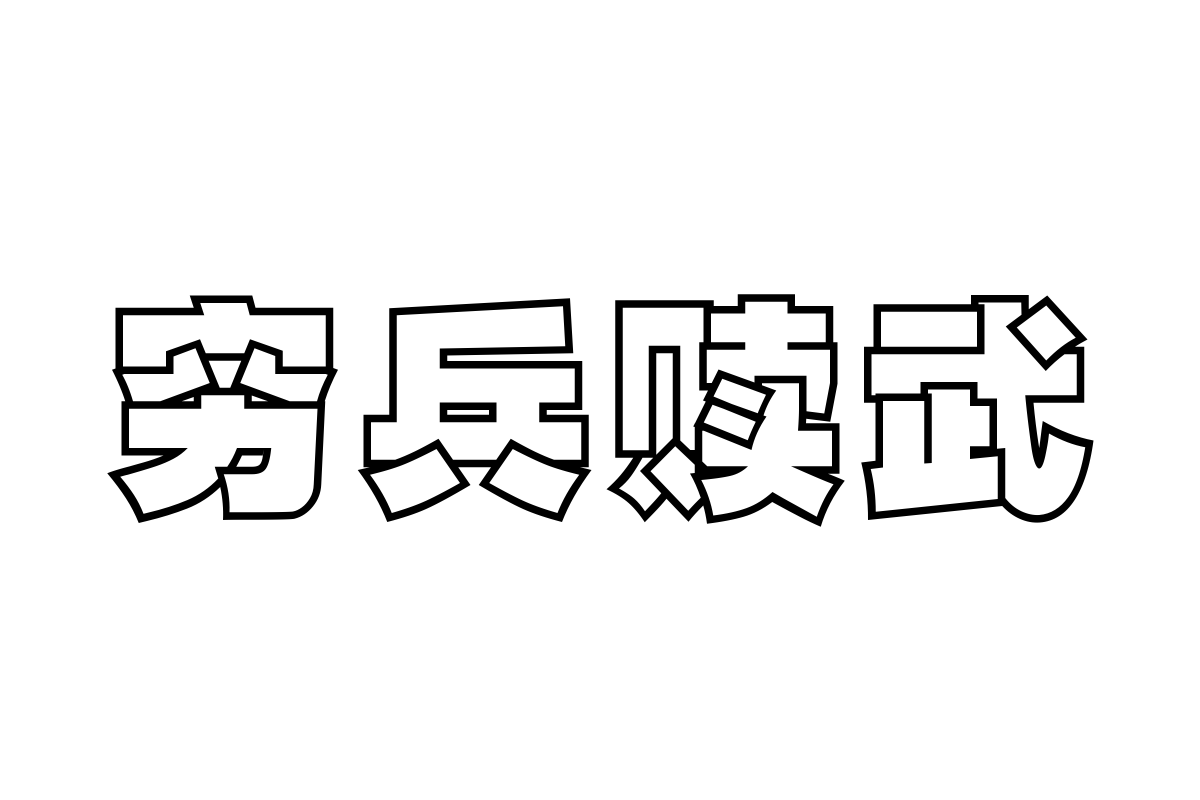
三极叠加黑字体,又称三极体字,是一种具有独特视觉效果的中文字体。它由三个不同的笔画组成,每个笔画都经过精心设计和调整,使得整个字体看起来更加美观、和谐。
这种字体的特点是笔画粗细不一,线条流畅自然。它的笔画既有粗犷的线条,又有细腻的笔触,给人一种强烈的视觉冲击力。同时,由于每个笔画都是独立的,所以这种字体在阅读时不会显得拥挤,也不会显得过于稀疏,给人一种舒适的感觉。
三极叠加黑字体适用于各种场合,如广告、海报、书籍、报纸等。它的使用可以使文字更加醒目,吸引人们的眼球。此外,由于其独特的视觉效果,它还常常被用于设计一些创意产品,如文具、装饰品等。